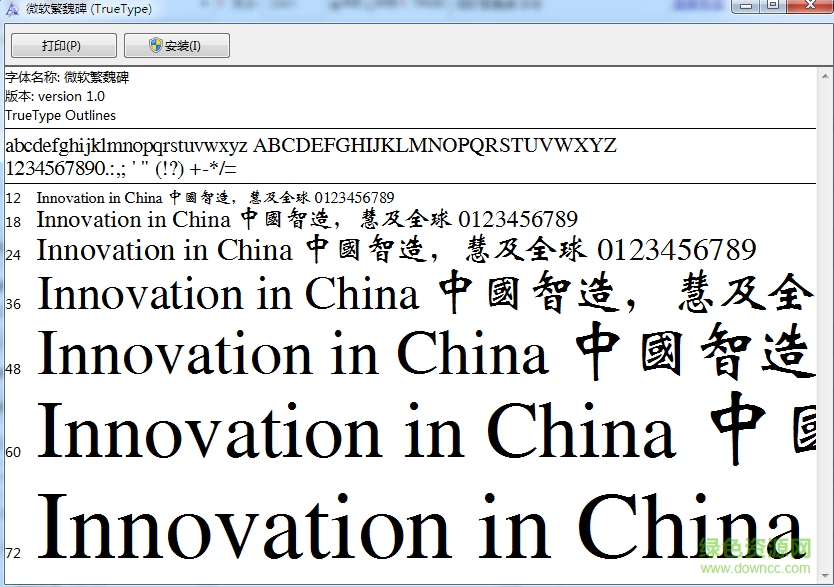
ctweibeisf字體是一款應(yīng)用廣泛的魏碑繁體字體,這款字體外形質(zhì)樸,筆畫遒勁,結(jié)體規(guī)范,有一種穩(wěn)重干練的氣質(zhì),需要的朋友快來下載吧!
魏碑書法筆劃嚴(yán)謹(jǐn)、樸厚靈動(dòng),豐腴不失于板刻,上承漢隸,下開唐楷,兼有隸楷兩體之神韻。它的書法藝術(shù)是在漢隸和晉楷的基礎(chǔ)上發(fā)展演化而來的,堪稱漢碑中的上品。古今書家對(duì)此碑都給予最高評(píng)價(jià),可謂漢碑集成之碑。